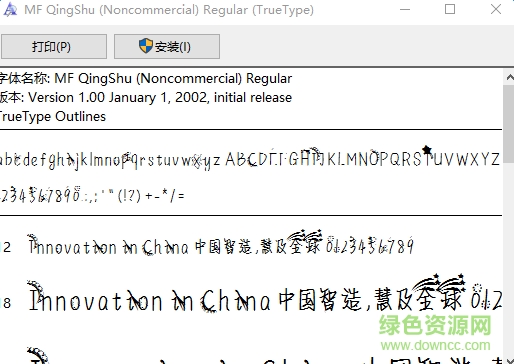
在星星下說(shuō)愛你字體是一款很有特色的電腦藝術(shù)字體,這種字體寫出來(lái)的字是很好看的,不僅字形美觀,實(shí)用性也強(qiáng),可以用于很多方面,歡迎大家來(lái)綠色資源網(wǎng)下載。
在星星下說(shuō)愛你字體是一款很不錯(cuò)的字體,小編已經(jīng)幫大家試用過(guò)了,寫出來(lái)的字效果真的很不錯(cuò),喜歡的朋友可以來(lái)綠色資源網(wǎng)下載。